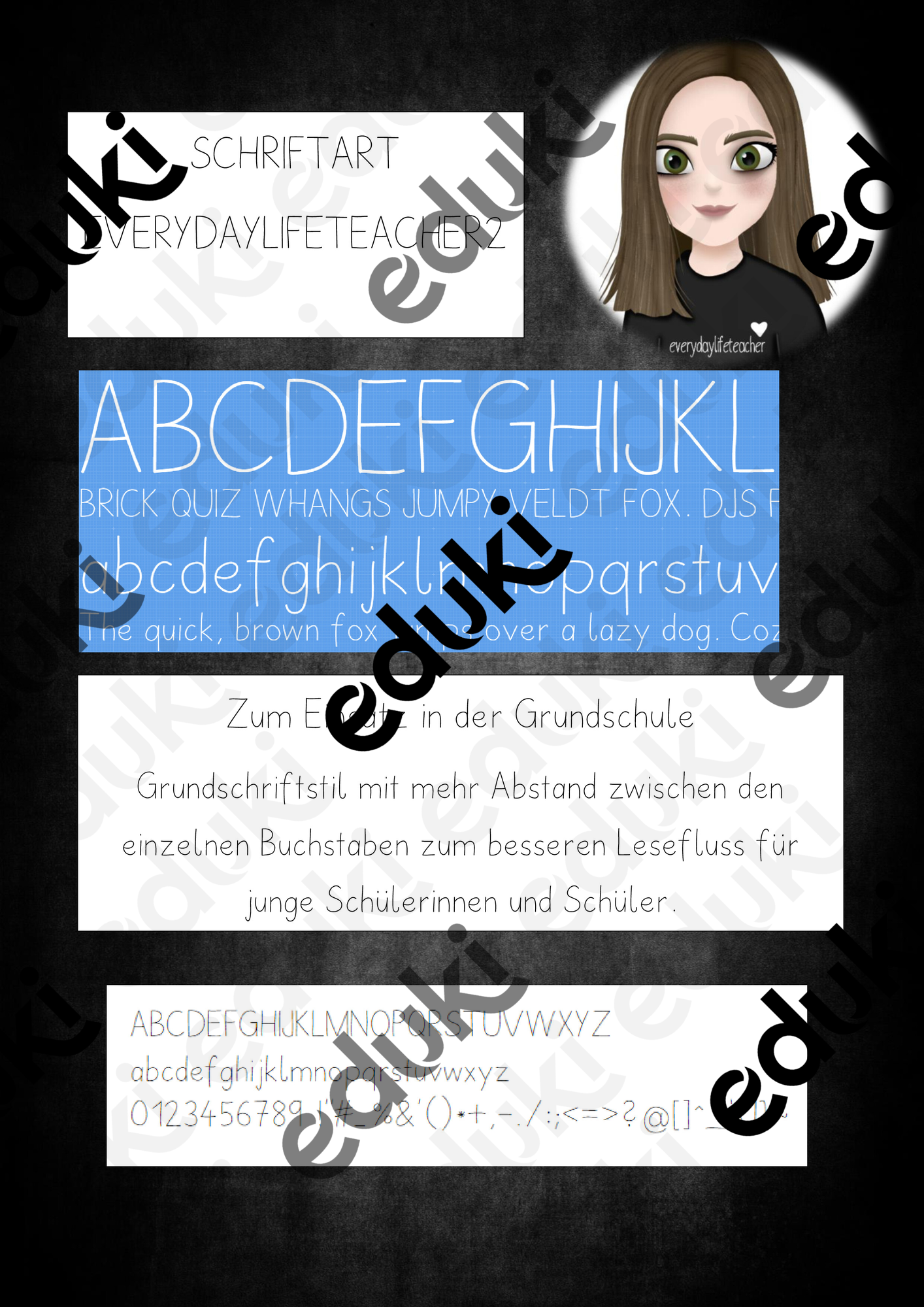
selbst erstellte Schriftarten - Schriftart everydaylifeteacher2 - everydaylifeteacher - Deckblatt
Hier könnt ihr euch meine Schriftart everydaylifeteacher2 downloaden. Sie ist im Grundschriftstil gehalten, mit mehr Abstand zwischen den einzelnen Buchstaben zum besseren Lesefluss für junge Schülerinnen und Schüler.
Schriftart everydaylifeteacher2